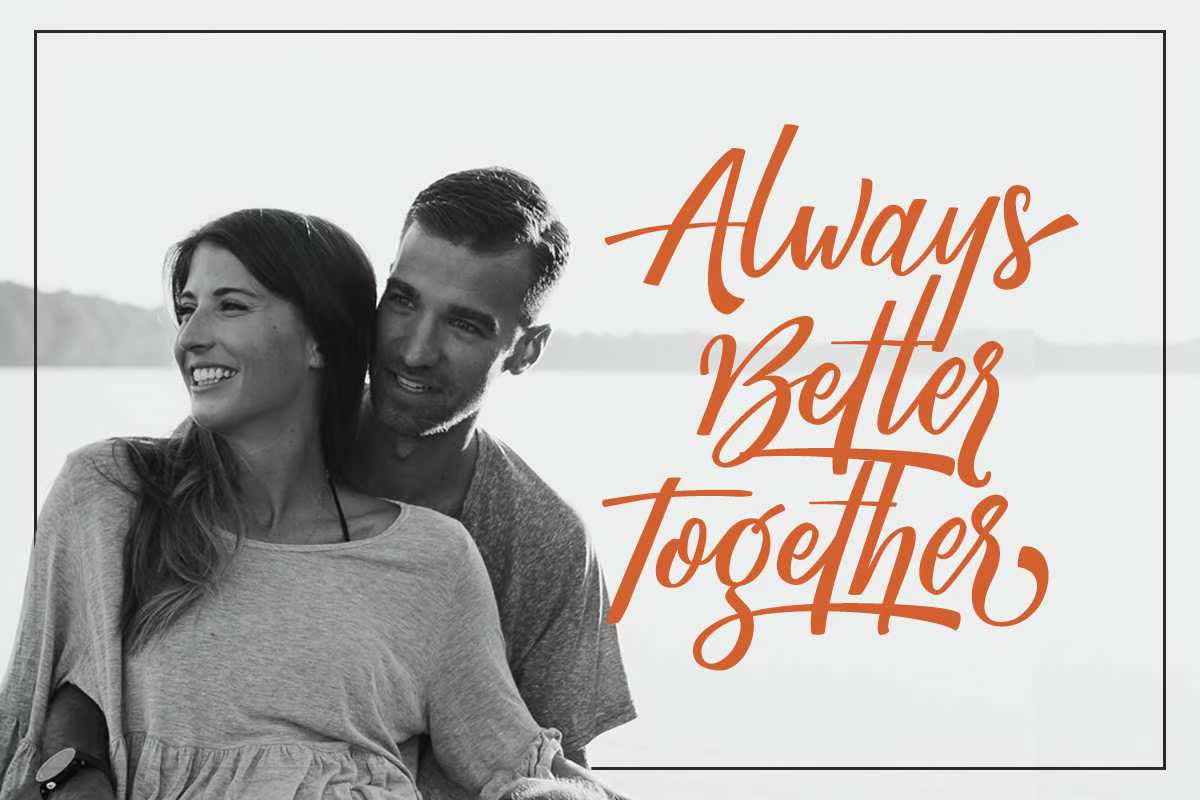
Megattortypeface。此字体非常漂亮,无需手动和书写。您只需在键盘上键入任何字体,就可以看到字体和线条的流动,从而创建出完美的手写体!它有许多开放式功能,包括:列表、样式替换和样式集,还支持多语言。此字体基于手动手写,适用于任何需要的设计,尤其适用于ScriptLogoTypeProject.Megattortypeface。此字体在书写和书写方面都非常漂亮。您只需键入任何键盘,就可以看到字体和内部线条的流动,从而创建出完美的手写体!该字体具有多种开放式功能,包括限制、替代样式和多种样式集,还支持多种语言。该字体基于手动手写,适用于任何设计需求,尤其适用于ScriptLogoTypeProject。